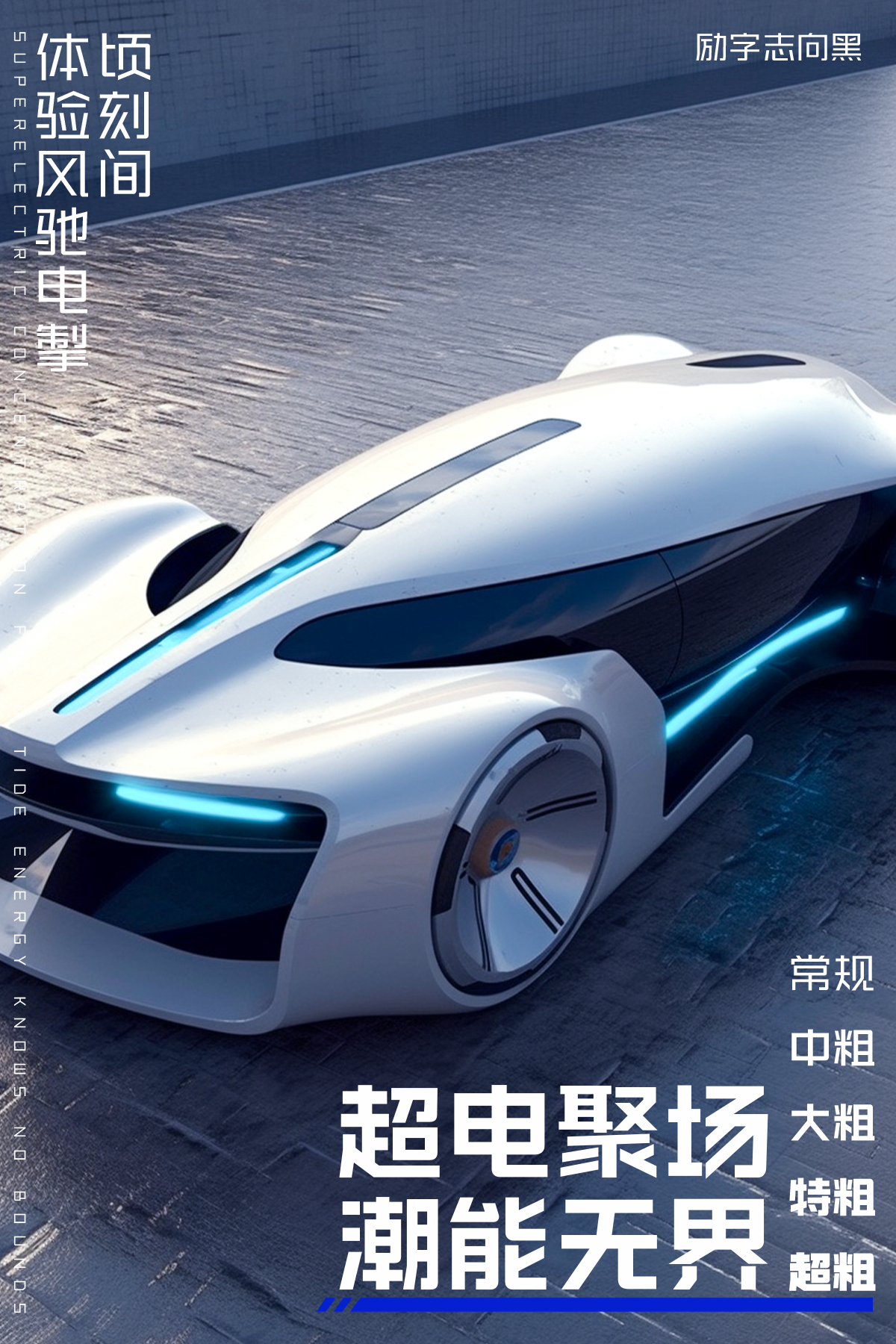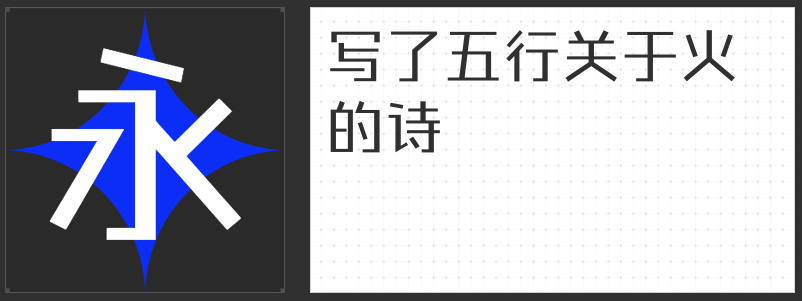
电商设计字体新宠:四款励字系列字体,打造视觉盛宴
在电商设计的广阔天地里,字体不仅是信息的载体,更是品牌个性的直接体现。今天,就让我们一同探索四款专为电商设计量身打造的励字系列字体,它们以独特的魅力,为电商视觉设计增添无限可能。
这款字体巧妙融合了圆体与黑体的精髓,通过在笔画拐角处增加的外圆角设计,赋予了字体稳重大气之中不失灵动的特质。字面充实饱满,结构稳定且适配屏显,无论是产品标题还是促销信息,都能轻松驾驭,让顾客在浏览中感受到品牌的温度与力量。
二、励字磅礴简 超黑
横看成岭侧成峰,这款字体以斜体与正体的创新融合,展现出“气势磅礴,万壑争流”的视觉效果。左侧倾斜的设计为稳重字形增添了动感,而右侧的垂直设计则稳固了整体架构,仿佛引领着顾客穿越千山万水,探寻品牌的无限魅力。在电商海报或主视觉图中使用,定能让人眼前一亮,难以忘怀。
以完美的斜度和利索的转折,这款字体展现出了独特的个性与力量。全直线的设计符合当代视觉审美,摒弃了过度的装饰,转而加强细节的优化,降低了阅读障碍,为顾客提供了更加舒适的阅读体验。在电商详情页或产品描述中,它将成为画面中的主角,独树一帜,引领潮流。
这款创意黑体字,以其粗壮的笔画和宽大的字面,带来了强烈的视觉冲击。饱满的块面感与折角圆设计相结合,犹如铁拳出击,横扫千军,展现出品牌不可一世的霸气与自信。在电商促销活动或品牌宣传中,它将成为吸引顾客眼球的利器,助力品牌脱颖而出。
这四款励字系列字体,各具特色,无论是稳重大气、气势磅礴,还是个性鲜明、霸气侧漏,都能为电商设计增添一抹亮色。选择它们,就是选择了一份专业与品质,让你的电商设计在众多竞争者中脱颖而出,成为顾客心中的首选。